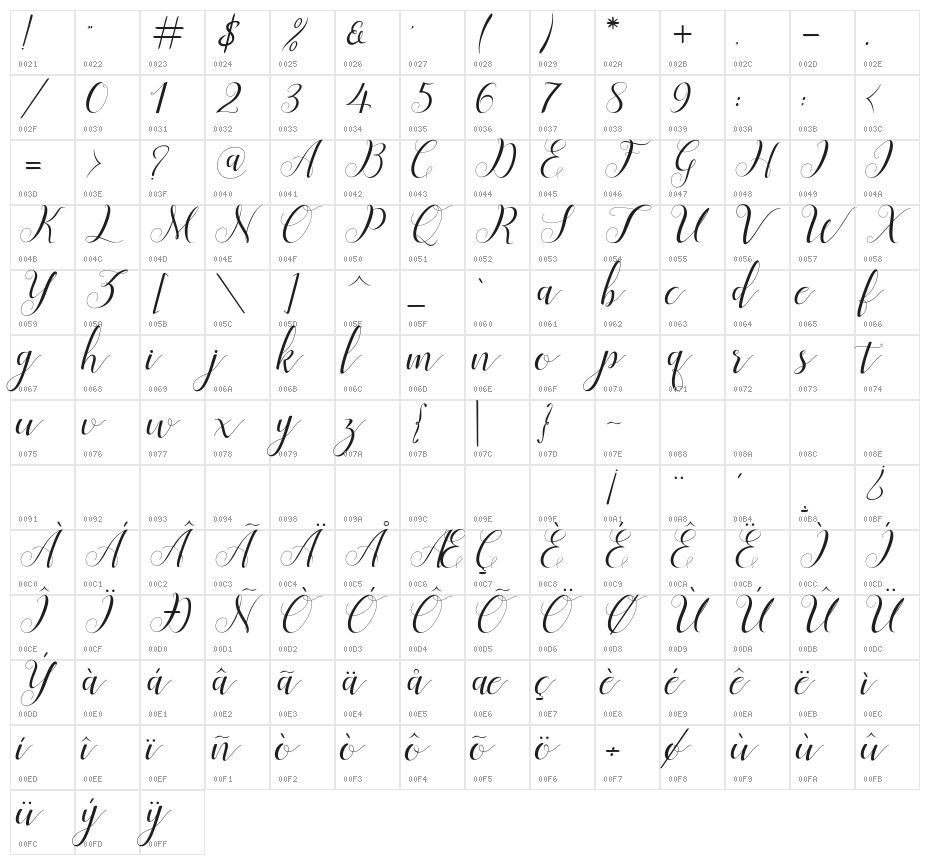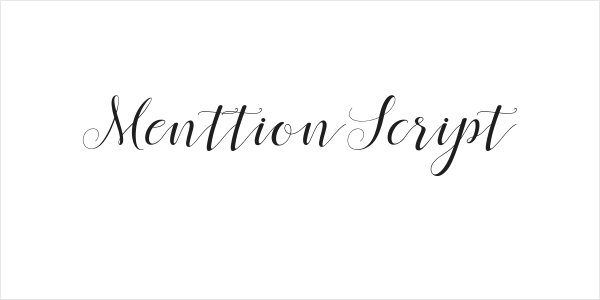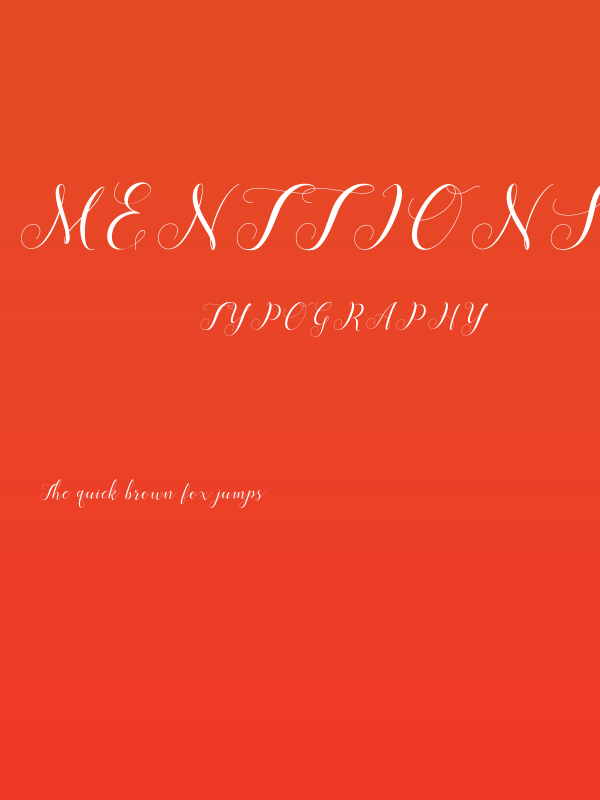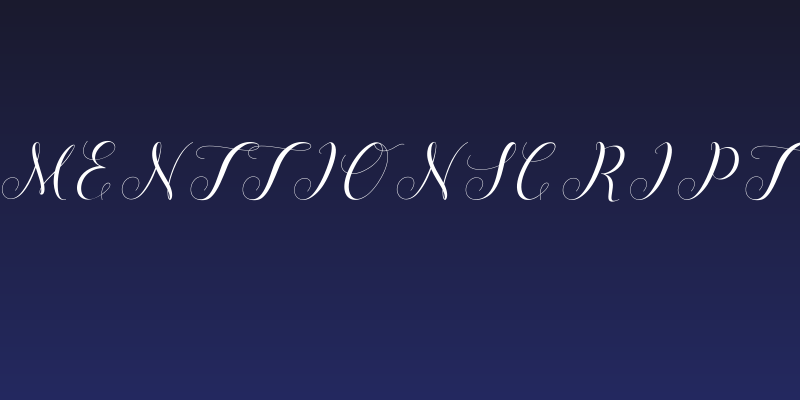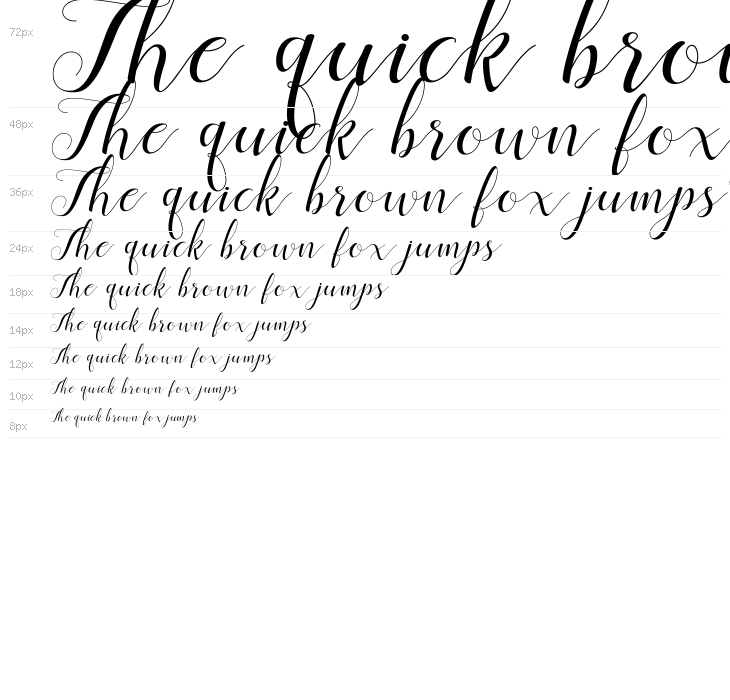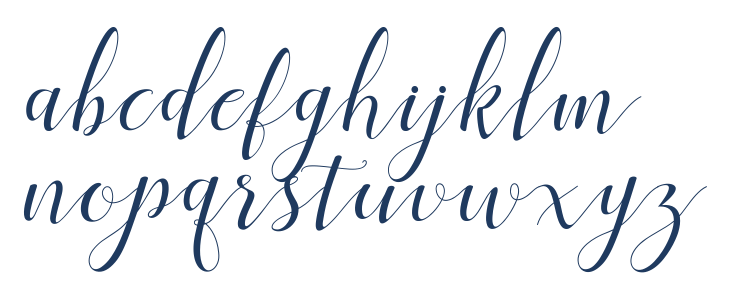
MenttionScript Font
✎ Script
| Gesamtstil | Elegant, Artistic |
| Anwendungsfall | Logos, Invitations, Decorative text |
| Vorgeschlagene Projekte | Ideal for wedding invitations, luxury branding, elegant stationery, and artistic posters. |